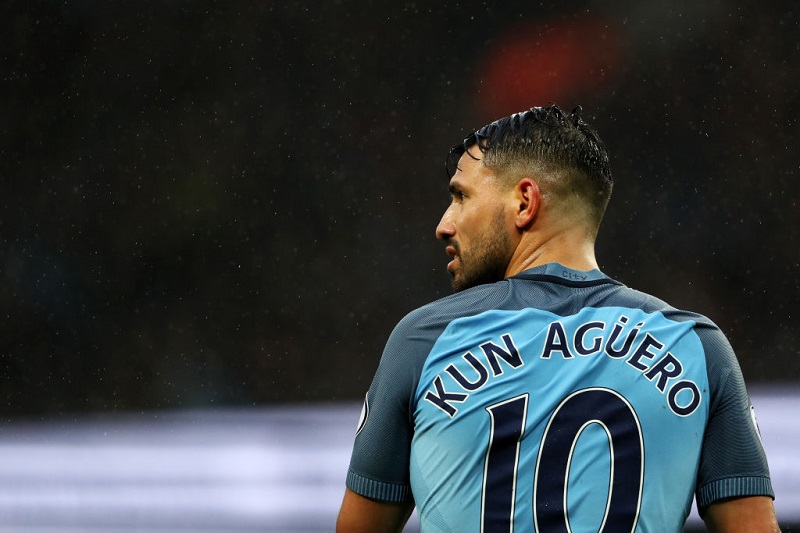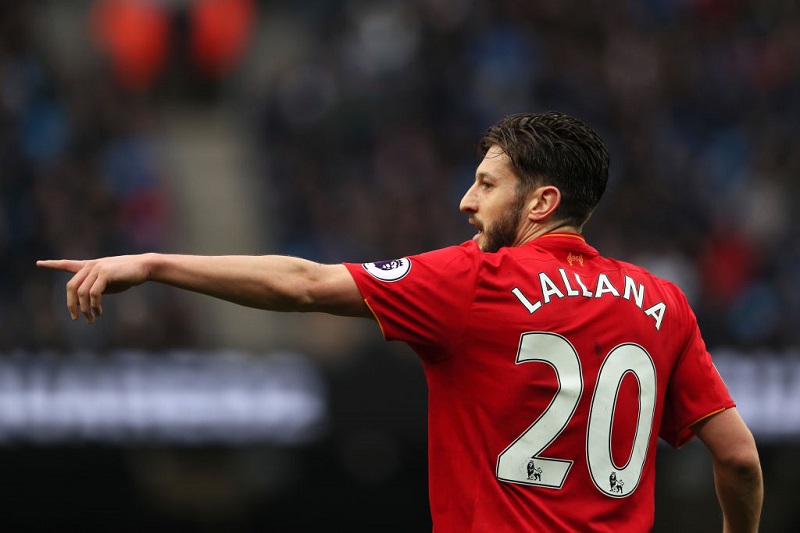
プレミアリーグは、各クラブのユニフォームに採用されているフォントが2017-18シーズンから変更になると発表した(ツイートで紹介されているのは今季のもの)。
プレミアリーグではオフィシャルパートーナーであるSporting iD社と共同でフォントを開発しており、今回はより現代的で活気のある新デザインを開発。
フォントが変更になるのはこの10年間で初めてのことで、配色のパターンは全部で5パターンあるという。
ちなみに、今季採用されているプレミアリーグの「独自フォント」はこんな感じ。
プレミアリーグのマネージングダイレクターを務めるリチャード・マスターズ氏は「あと数ヵ月で各クラブがそれぞれ新しいユニフォームを発表し、そして新しいフォントや配色が見られるのが楽しみだ」をコメントしている。